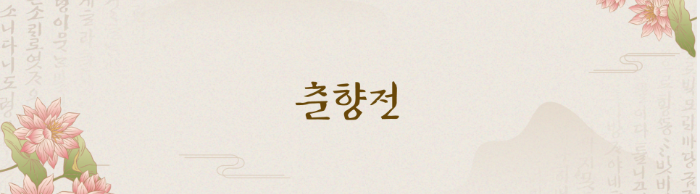
뿌리깊은 프로젝트의 일환으로 (주)디자인210에서 시대별 의미있는 글씨를 연구하며 뜻을 이어가고자 석보상절을 시작으로 앞으로 출시되는 뿌리깊은 서체들이 3년간 개발, 런칭, 배포된다고 합니다. 그 열번째 폰트인 춘향전은 다음과 같은 내용을 담고 있습니다.
- 한국서민문학의 대표적 작품으로 작자,연대 미상의 설화를 바탕으로 한 소설
- 다양한 판본 중 필사본의 특징으로 획이 끊기지 않고 중성과 종성이 연결되는 특징을 지님
- 우리나라의 많은 사람들이 사랑하는 조선시대 최고의 로맨스 소설